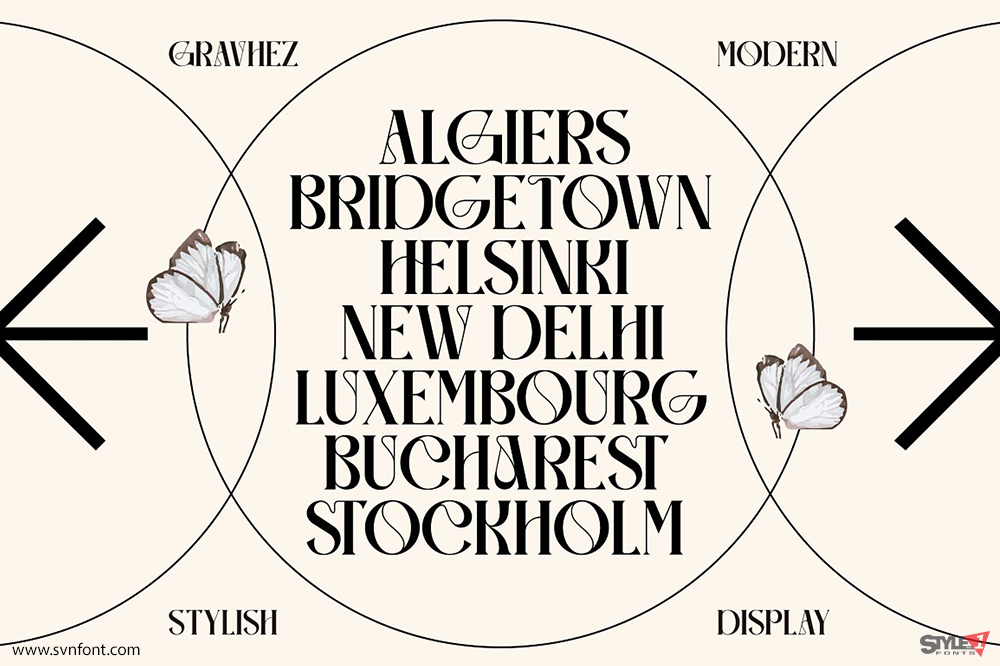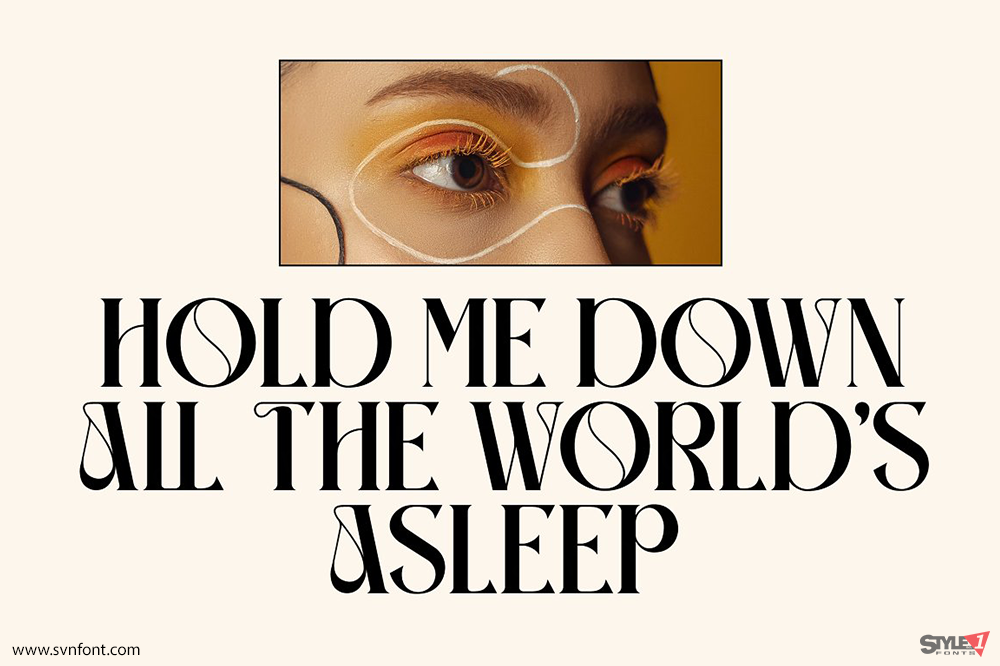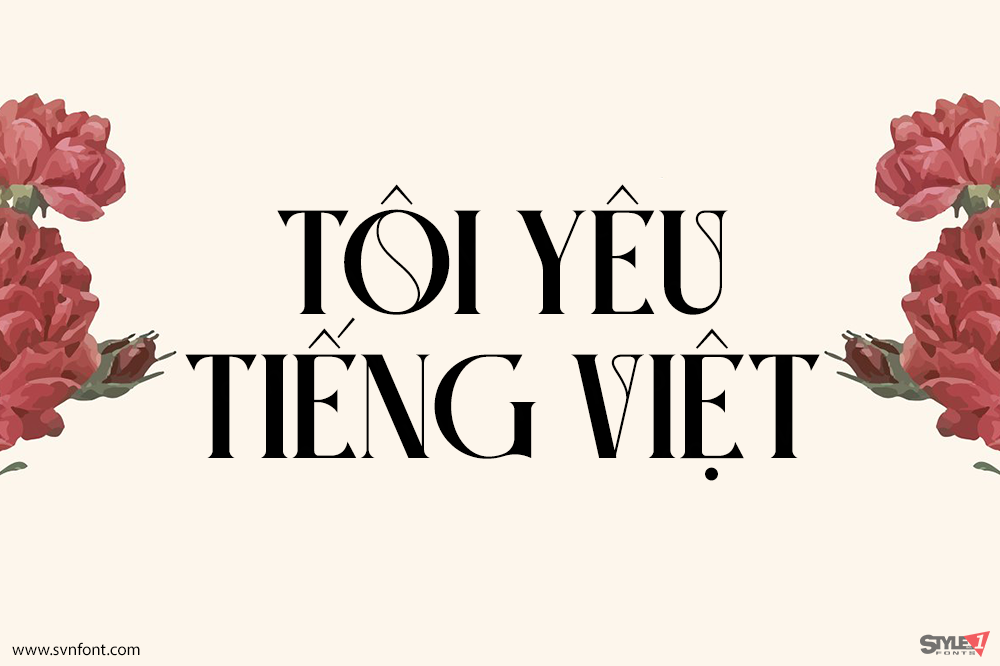
GRAVHEZ Typeface được giới thiệu đầy tự hào bởi Storytype — một typeface serif mang phong cách hiện đại pha cổ điển, sở hữu cá tính riêng và diện mạo thời thượng. Font đặc biệt phù hợp cho logo sang trọng, cao cấp, thiết kế tựa sách hoặc phim, thương hiệu thời trang, tạp chí, quần áo, lettering, trích dẫn và nhiều ứng dụng sáng tạo khác.
Nhà thiết kế: Heru Utama Putra
Nhà phát hành: Storytype Studio